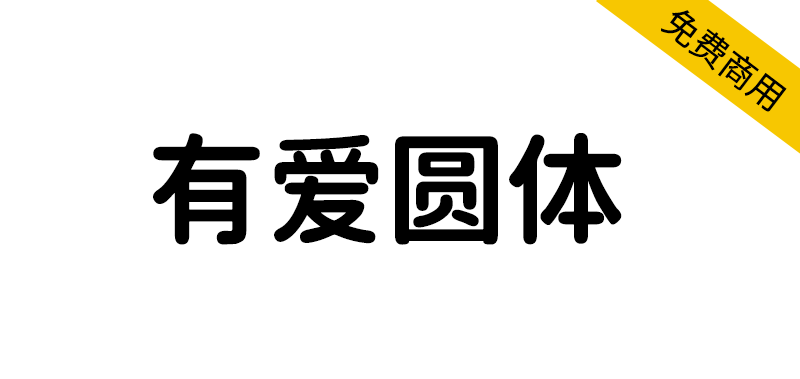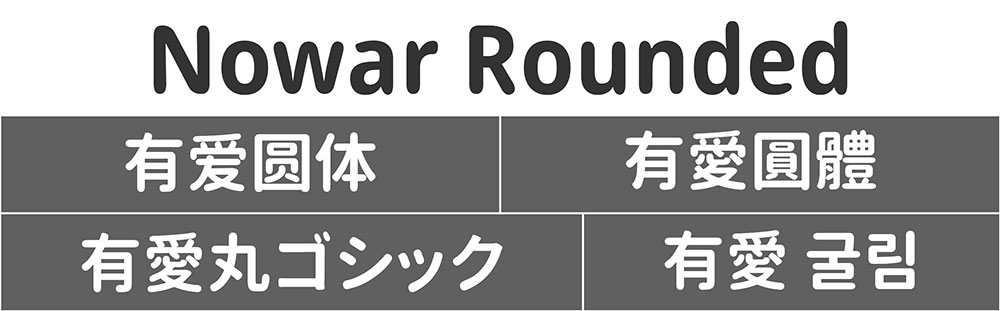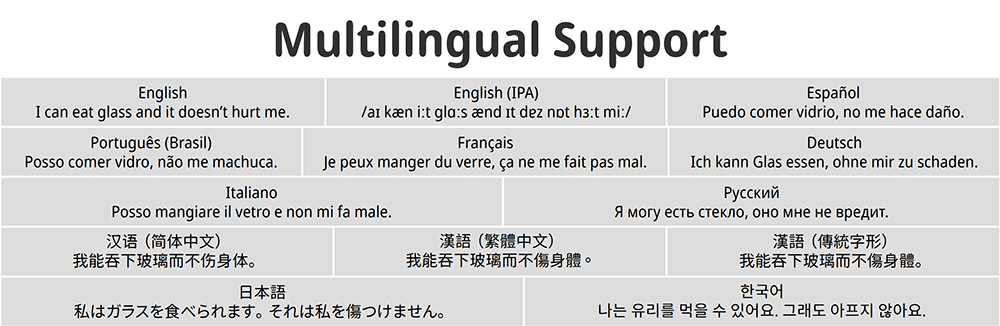
有爱圆体(Nowar Rounded)是《魔兽世界》和《魔兽世界:经典怀旧服》字体包,是由Noto Sans和资源圆体的合并而来的字体。有爱圆体也从思源黑体衍生而来,所以,在中文字形上有爱圆体和资源圆体差不多。但是有爱圆体只有四个字重,分别是Light,Regular,Medium,Bold,要比资源圆体少些字重。